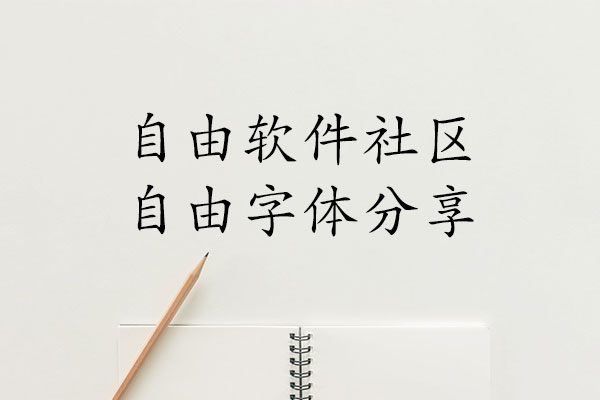
文鼎PL简中楷
文鼎科技免费提供的文鼎PL简中楷和文鼎PL中楷体(BIG5)是两套优秀的开源楷体字体,它们也是Linux上最早的高质量开源中文字体。这两款字体的主要区别在于,文鼎PL简中楷更加注重简体汉字的呈现,而文鼎PL中楷体(BIG5)则更加注重繁体汉字的呈现。因此,对于中国大陆的用户来说,文鼎PL简中楷可能是更好的选择。
文鼎PL简中楷效果预览